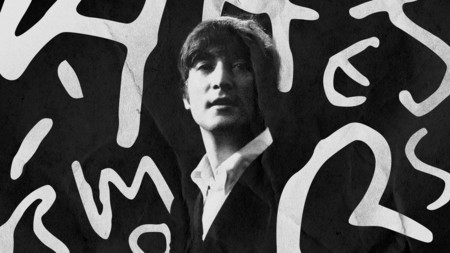
Escribe con la letra de John Lennon o David Bowie descargando estas tipografías de estrellas de la música gratuitas
Leonard Cohen, David Bowie, John Lennon, Kurt Cobain y Serge Gainsbourg han escrito algunas de las canciones más inolvidables de la historia de la música.
Songwriters Fonts es un proyecto creado por el diseñador gráfico francés Nicolas Damiens y el redactor Julien Sans. Juntos han publicado unas tipografías que permiten a cualquier escribir con la letra de estos genios.
El diseño de la web es realmente impecable, y en ella podemos encontrar los archivos con cada una de las tipografías. Sobre Kurt Cobain afirman que "su manera única de escribir afectó a una generación para siempre".
De Bowie declaran que "nunca dejó de experimentar" y aseguran utilizar estas tipografías "con la escritura de compositores influyentes puede ayudar a desarrollar la la imaginación".
"Puede ayudar a desarrollar la imaginación".
A continuación dejamos el acabado (en mayúsculas y minúsculas) de cada una de estas tipografías:
Songwritersnotes Davidbowie Graphicdesign Itsnicethat 0 Tipografía de David Bowie.
Songwritersnotes Johnlennon Graphicdesign Itsnicethat 02 Tipografía de John Lennon.
Songwritersnotes Kurtcobain Graphicdesign Itsnicethat 03 Tipografía de Kurt Cobain.
Songwritersnotes Leonardcohen Graphicdesign Itsnicethat 0 Tipografía de Leonard Cohen.
Songwritersnotes Sergegainsbourg Graphicdesign Itsnicethat 02 Tipografía de Serge Gainsbourg.